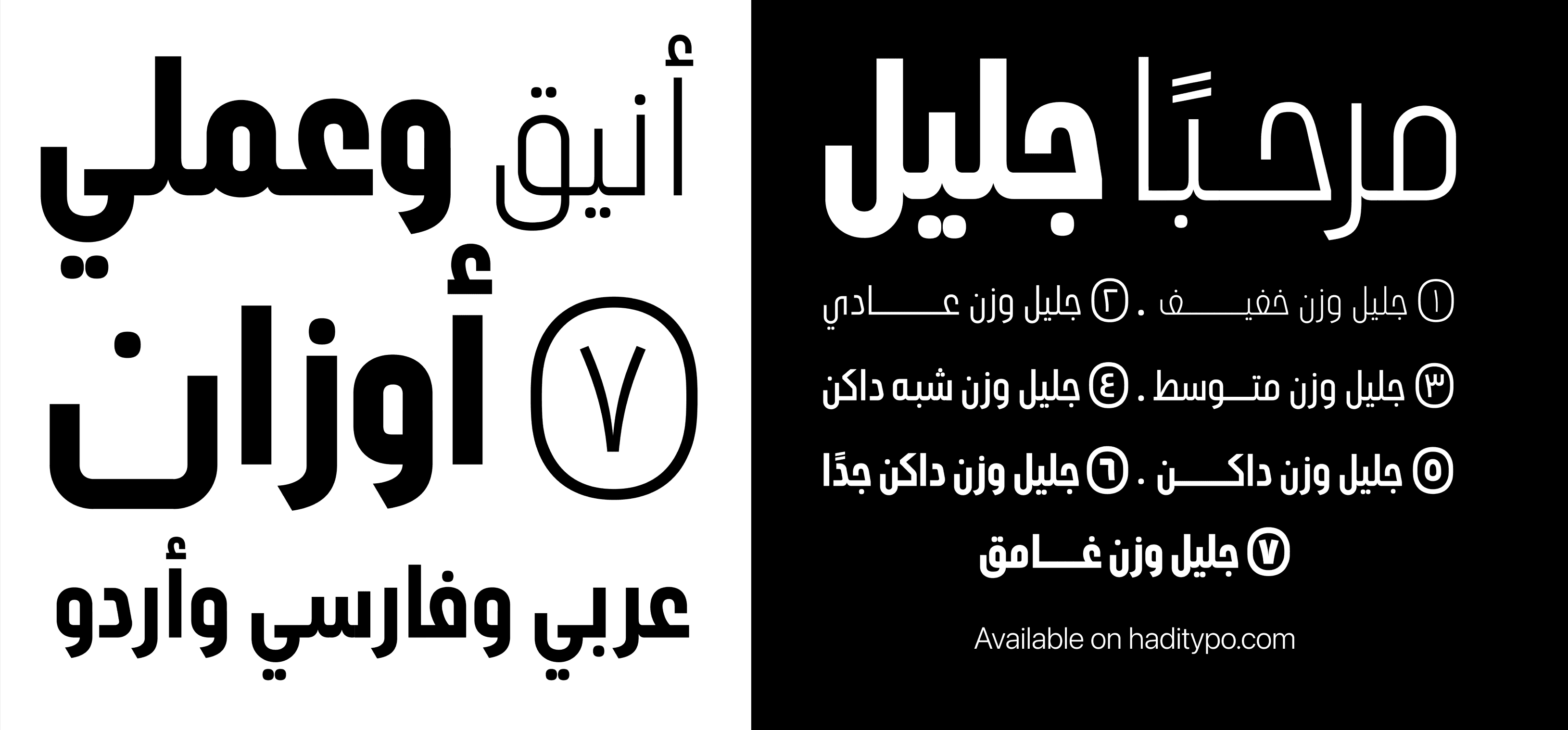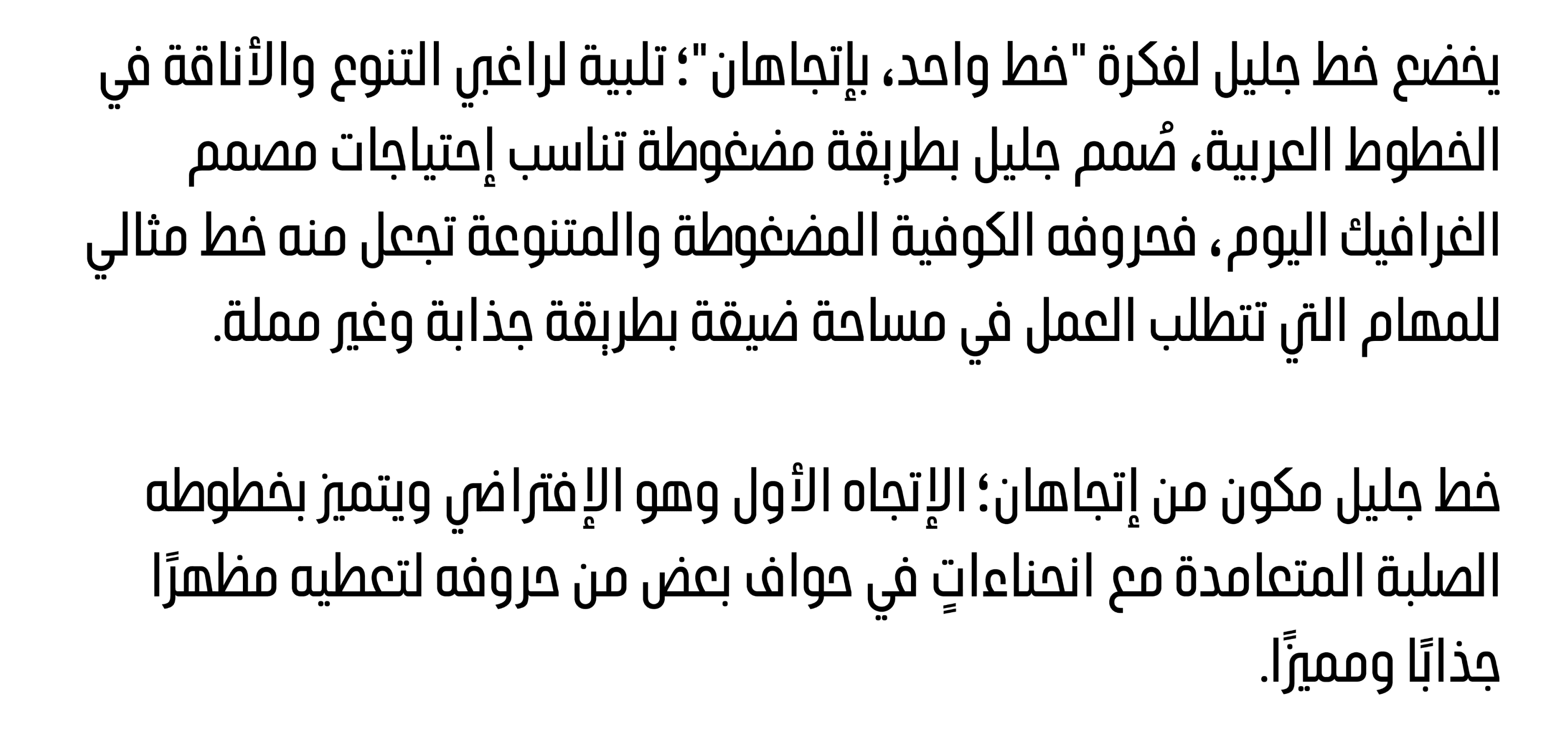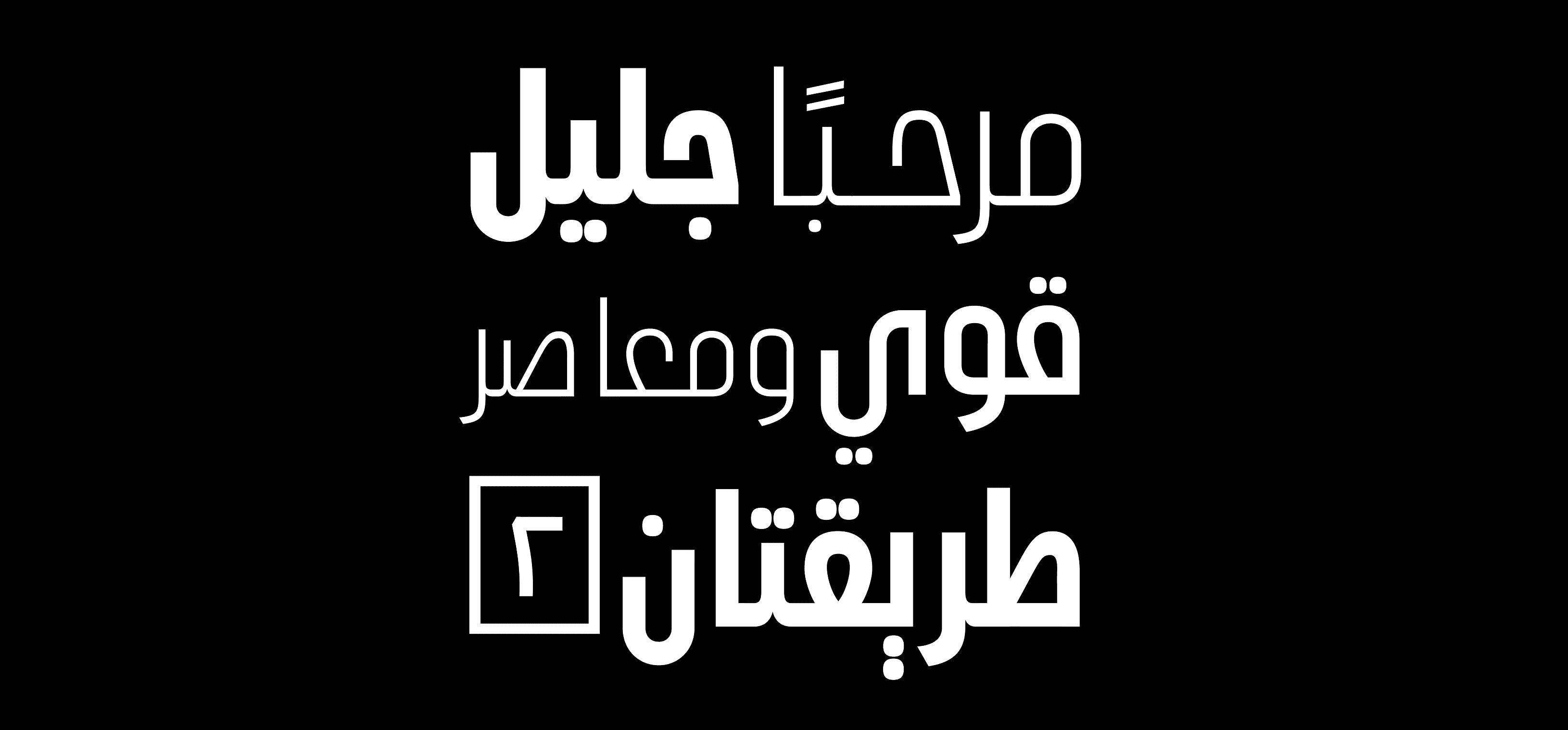
خط HT جليل – HT Jaleel Typeface
عائلة خطوط مكوّنة من 7 أنماط متراصة ومتجانسة، من تصميم محمد هادي، تتميز ببنية هندسية موحّدة وتوزيع بصري مدمج.
الحروف الديناميكية تتّخذ طابعًا مضغوطًا، حيث تتحول الأشكال الدائرية إلى خطوط مستقيمة عمودية، مما يمنح النص مظهرًا انسيابيًا وعصريًا.
توفر الأوزان السبعة تدرجات متباينة تتيح خلق تأثير بصري قوي عند المزج بين النمط الأخف والأثقل.
كل نمط في الخط يدعم الروابط الحرفية (conjuncts) والتركيبات (ligatures) بشكل كامل، مما يجعله مثاليًا للتصميم التحريري، والطباعة الجريئة، والعناوين الحديثة.